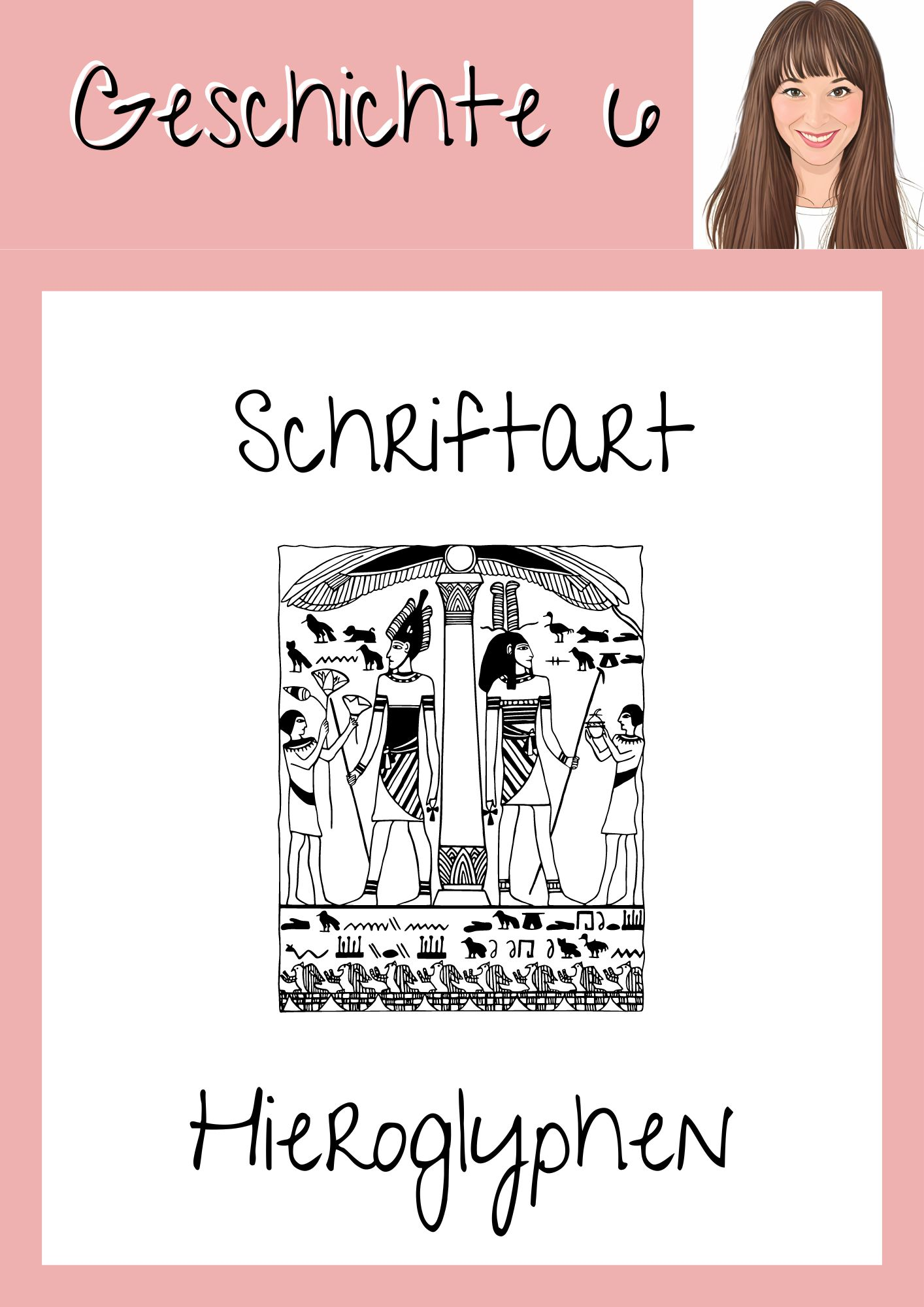
selbst erstellte Schriftarten - Schriftart Hieroglyphen - mrs.easy.teaching - Deckblatt
Ich habe hier das Standard-Alphabet (A-Z) in Hieroglyphen "übersetzt".
Schriftart Hieroglyphen